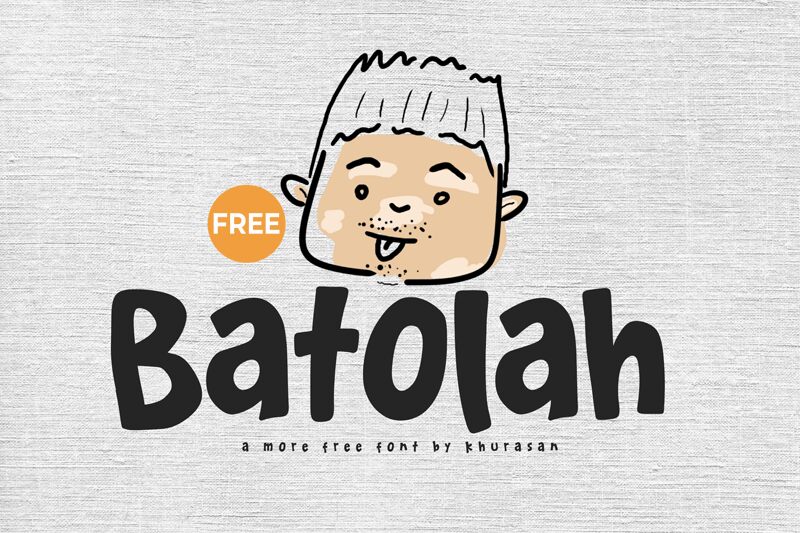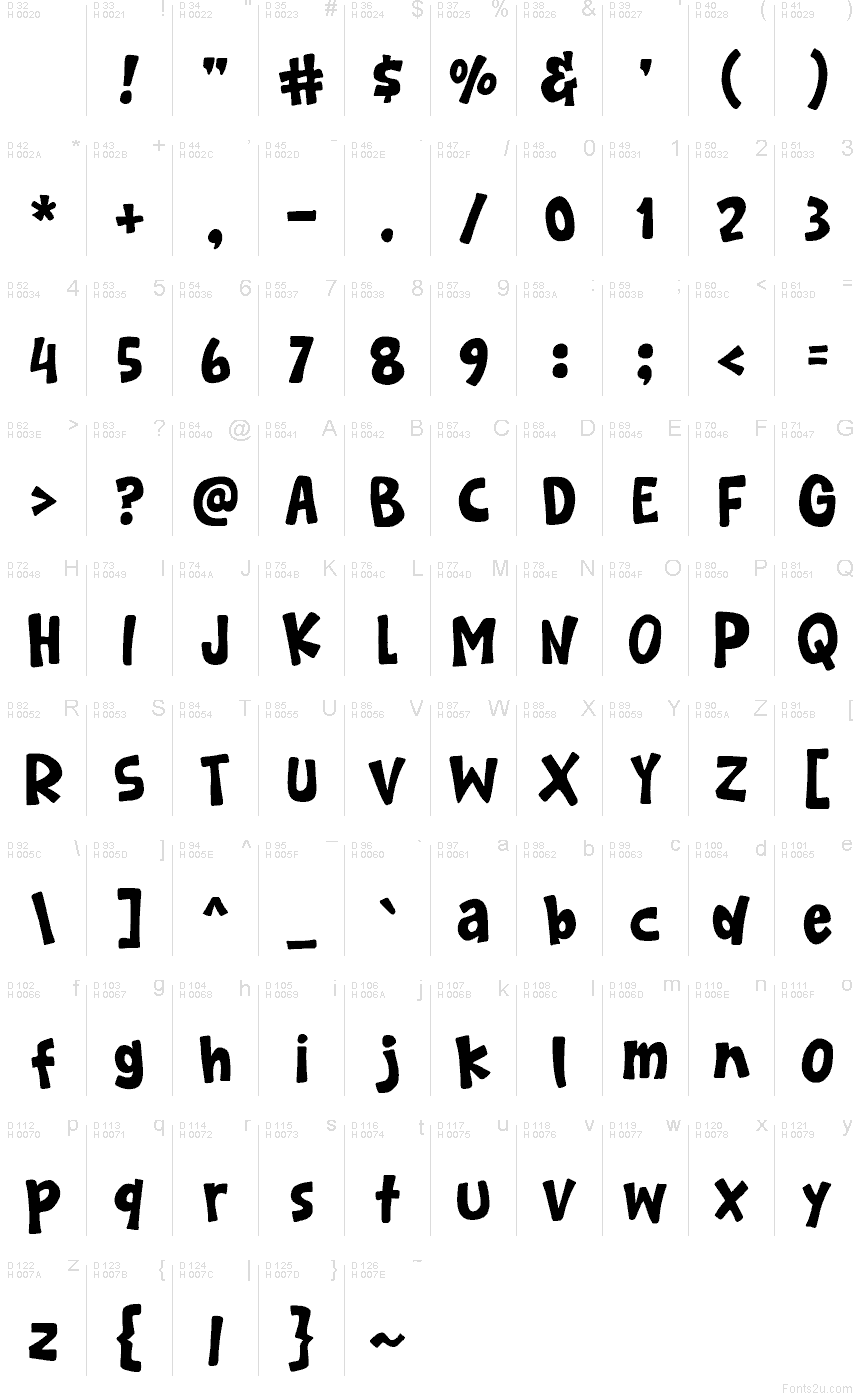
Batolah autorstwa Khurasan to darmowy krój pisma typu display w stylu cartoon, wyróżniający się radosnym, ręcznie rysowanym charakterem. Litery są masywne i miękkie, z zaokrąglonymi kształtami, lekko nieregularnym rytmem i wysokimi pociągnięciami, które nadają projektowi zabawną, niemal komiksową energię, nie przytłaczając przy tym odbiorcy.
To sprawia, że Batolah jest naturalnym wyborem do opakowań dziecięcych, naklejek, zaproszeń urodzinowych, nagłówków na plakatach oraz ciekawych tytułów w mediach społecznościowych. Jako darmowy font, sprawdza się najlepiej tam, gdzie jego duże, obłe kształty mogą grać główną rolę — krótkie hasła reklamowe, teksty na okładki czy karty tytułowe doskonale współgrają z jego swobodnym, przyjaznym stylem.